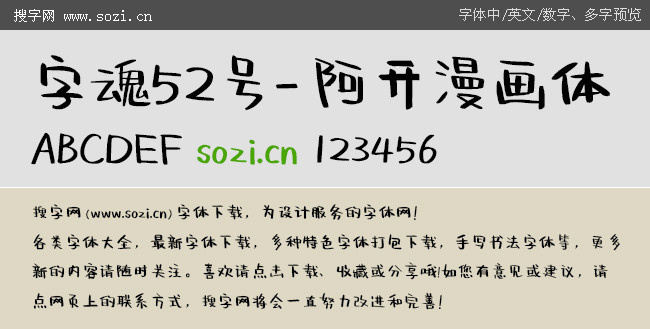
字魂52號(hào)-阿開漫畫體
搜字網(wǎng)提供一款字魂52號(hào)-阿開漫畫體中文字體下載,該字體是一款硬筆手寫卡通字體,該字體包含6763個(gè)中文、字母、 符號(hào)和數(shù)字,具有創(chuàng)意、快樂、童真、趣味 的風(fēng)格,可以滿足您設(shè)計(jì)上的各種需求,該字體主要用于書籍、報(bào)紙、游戲、動(dòng)漫、H5 等場(chǎng)景。